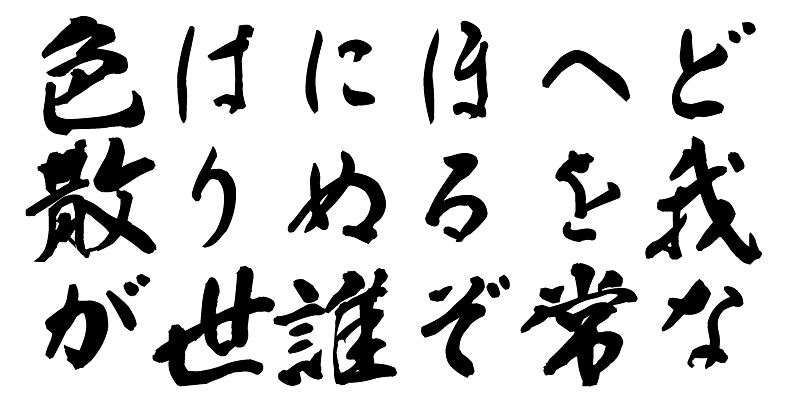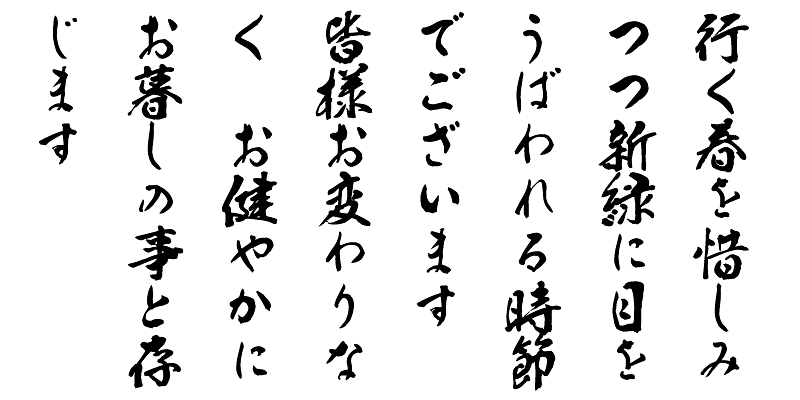
Questo font include i primi 1.000 caratteri kanji scelti dalle tabelle di frequenza dei caratteri realizzate da società di giornali, case editrici e istituti di ricerca linguistica, oltre a 206 caratteri kana e segni di punteggiatura.
Questa serie di font contiene caratteri tipografici giapponesi originali scritti a mano e basati sulla calligrafia a penna lanciati nel 2002. Con il loro aspetto caloroso, questi caratteri attireranno l’attenzione del lettore sui punti chiave di un design.